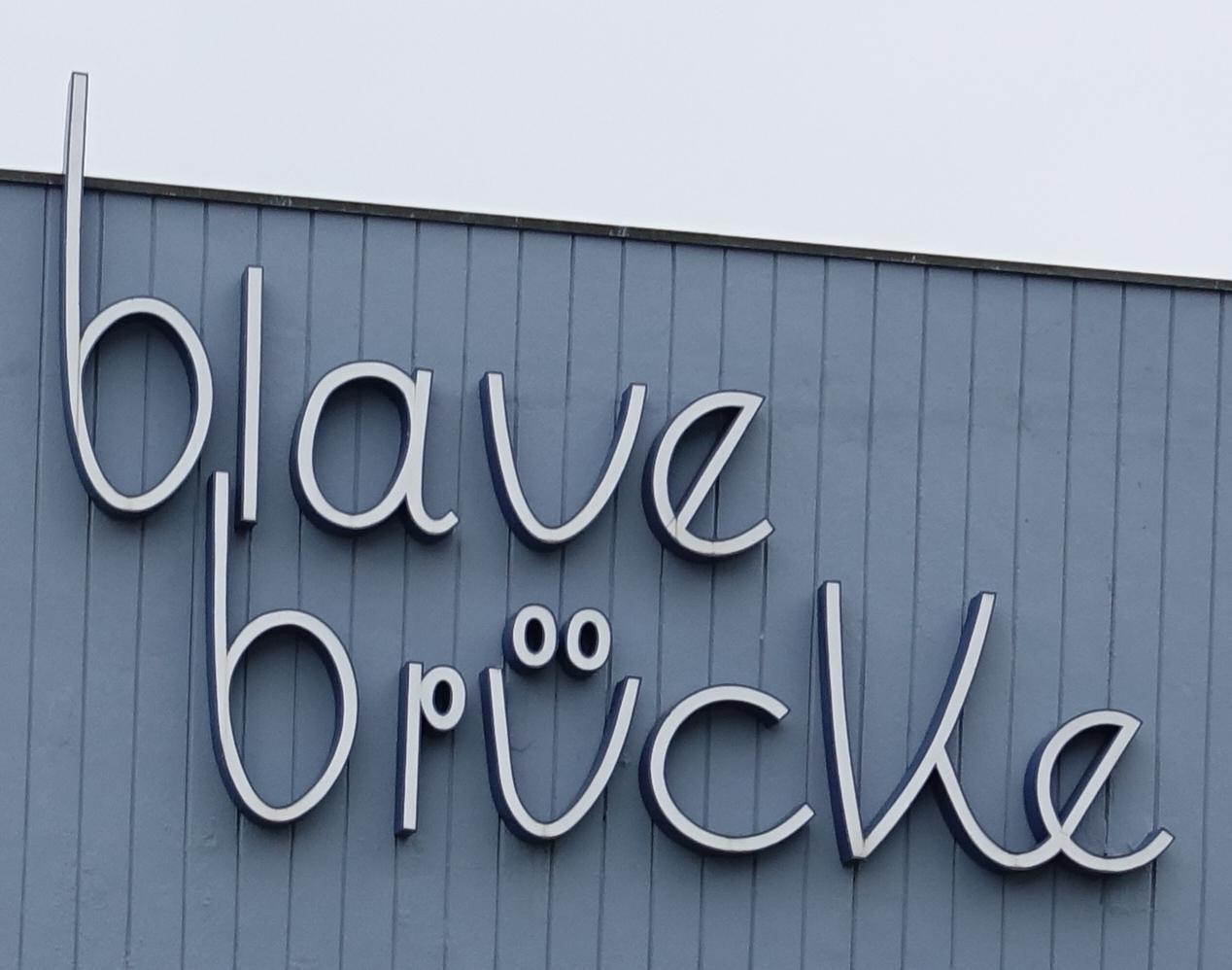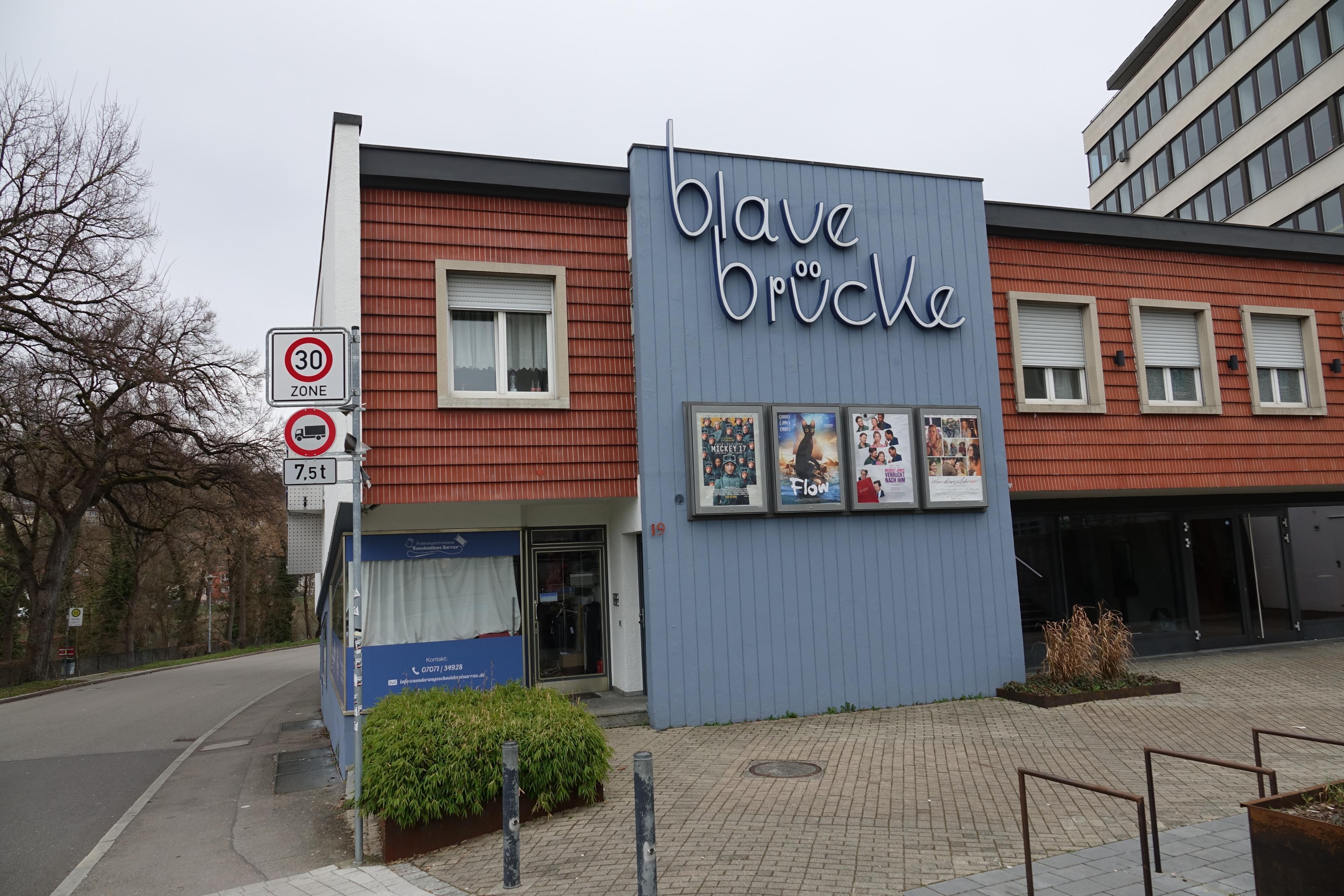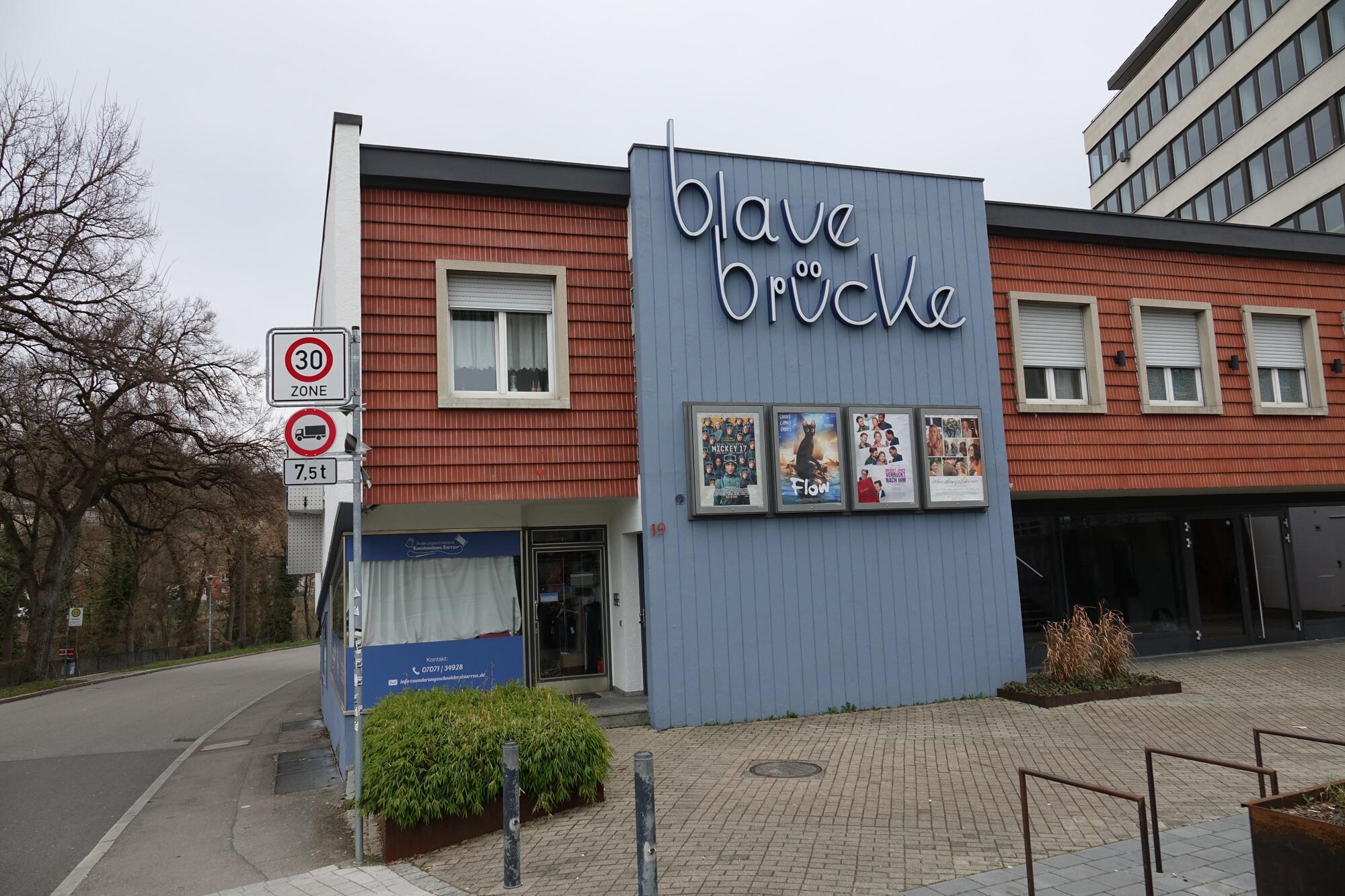
Suche die Schriftart vom legendären "blauen Brücke" Kino in Tübingen
Ich suche die exakt identische Schriftart vom Kino "blaue Brücke" in Tübingen.
Gibt es irgend einen Hinweis, dass das tatsächlich ein digitaler Font ist, und nicht "einfach nur" eine Schildermacher-Arbeit "ab Handzeichnung" für diese beiden Worte?
Ja, die "b" sehen identisch aus, kann aber auch einfach 2x gefertigt worden sein. Beim "e" ist es schon nicht so sicher, und "u/ü" sind nicht gleich geschwungen.
Falls das kein Font ist: brauchst du einen solchen für andere Wörter (mit der Gefahr, dass nicht viele andere Begriffe gut aussehen werden, das ist oft eine herbe Enttäuschung), oder einfach nur eine Digitalisierung des vorliegenden Schriftzugs um ihn wo anders verwenden zu können (das wäre mir vertretbarem Aufwand für jeden Grafiker machbar)?